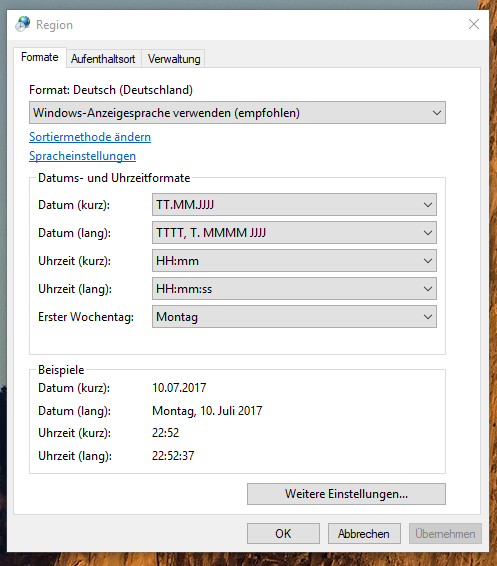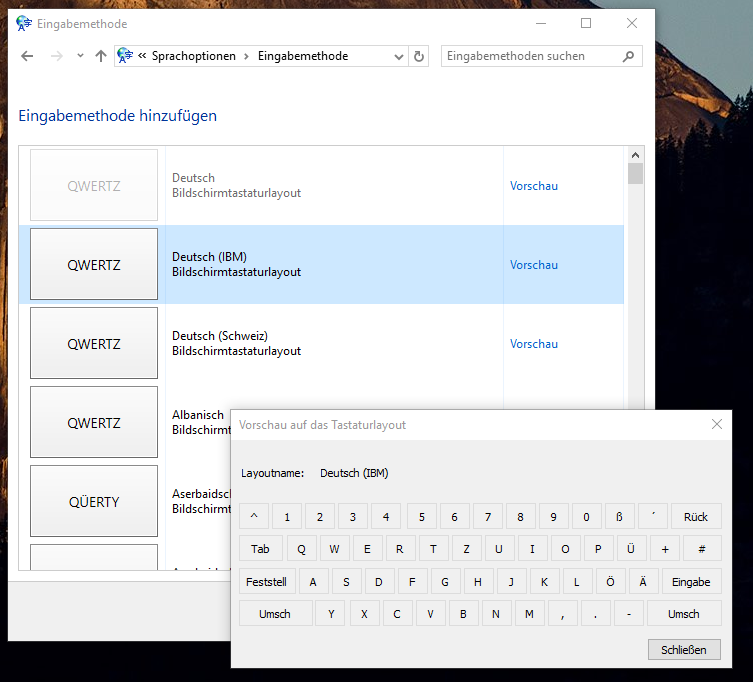
Das Versal-Eszett sieht aus wie eine Taube, die einen dicken Bauch hat.
Die Taube will mit ihren Flügeln das E umarmen, um sich an dessen Schulter auszuheulen ...
Nix Taube oder Robbe – das ist ein waschechter ẞ-Pinguin ;-)
Auf jeden Fall richtig übel.
Für das große ß reicht schon eine Tastatur nach T2, es wird durch Alt Gr und H gebildet. Allerdings verkauft momentan nur der Hersteller Cherry aus Auerbach in der Oberpfalz so ein Gerät in der T2-Version. […]
Die Tastatur-Firmen warten darauf, dass die DIN-Norm für die Standards aktualisiert wird. Momentan arbeiten der Normenausschuss Ergonomie und der Normenausschuss Informationstechnik und Anwendungen vom DIN an einer Lösung für das ß-Problem. Bis sie so weit sind, kann es aber noch einige Wochen dauern. Es soll Überlegungen geben, das Grad-Zeichen, also den kleinen hochgestellten Kreis, durch das große ß zu ersetzen, heißt es von der Firma Cherry. Damit befände sich das große ß am linken Rand der Ziffernleiste neben der Eins, das kleine wie gehabt am rechten Rand neben der Null.
Nun, schon vor einiger Zeit hatte ich ja schon einen modifizierten Tastaturtreiber im Programm:
Hier hatte ich mich für die Position Shift + AltGr + ß entschieden. Dieser Tastaturtreiber, bei dem ich auch das lange s auf AltGr + s und auch den ZWNJ auf AltGr - gelegt habe, sowie einige weitere Ligatuten und Sonderzeichen aus der Fraktur-Umgebung.
Leider lässt sich auf Windows10 kein soch privater Tastaturtreiber mehr installieren, aber meine Position des ẞ haben sie übernommen :-) Schade ſ und den ZWNJ hab ich da dann nicht mehr.
Aber immerhin hat ẞ da schon sein zuhause gefunden, und aus meiner Sicht ohne Umgewöhnung.
Mein Lieblingsplatz wär allerdings der Platz des "?" welches man ja auf AltGr+1 (also neben "!") verlagern könnte, dann wären ß und ẞ auf der gleichen Taste genau wie andere Buchstaben vereint. Eine andere Lösung: ß und ẞ werden auf die Taste neben ö, also # ' verlegt, und diese Zeichen rutschen auf den bisherigen Platz vom ß, wodurch ßẞ dann bei den Buchstaben lägen, wo sie eigentlich hingehören würden.
Ich finde die Belegung von Windows 10 am sinnvollsten. Das Zeichen ist dort, wo wir das ß sowieso wissen.
Ach ja, käme das Fragezeichen auf die 1-Taste als AltGr+1, könnte man auf Shift+AltGr+1 auch noch das Interrobang unterbringen, das hätte dann auch eine Logik.
Drum hatte ich mich ja für exakt die gleiche Lösung entschieden, ohne vorhandenes weg zu schubsen.
Bei meinem alternativen Tastaturlayout ist das ẞ da, wo es logischerweise hingehört, nämlich auf der Zweitbelegung von ß.
Für eine Qwertz-Belegung würde ich es entweder auf ß oder s packen.
Die Sache mit Windows 10 kann ich jetzt von meinem Rechner nicht beurteilen, da ich dies nicht installiert habe.
Nein, auf aktuellem Windows 10 Version 1703 kommst du nicht mehr auf die Auswahlseite mit den verschiedenen Tastaturlayouts. Hier ist nur noch eine Sprachauswahl, und Windows holt dann den betreffenden Tastaturtreiber von der Windows-Update Seite. Dafür ist aber ẞ offiziell auf Shift AltGr ß gekommen.
Bei Build 1607 ging es noch.
Dieses Fenster gibt es nicht mehr:
Statt dessen hat die Systemsteuereung bei Region nur noch dies:
und die Sprachoptionen - Eingabemethode bietet nur das:
Nur die Windows-eigenen Tastaturlayouts, und in der Vorschau sieht man auch nicht die Shift/AltGr-Belegung.
Auf der Mac-Tastatur wäre bei alt-shift-w noch Platz (da wäre es immerhin in Nachbarschaft zum ∑) ... da ist jetzt bloß eine von diesen nervigen Anführungszeichen-Dopplungen :party:
M.E. ist der Ascii-Zirkumflex auf der Taste ganz li. oben [°] für die deutsche Tastatur entbehrlich.
Wie findest Du diesen Vorschlag?
Ich vertraue darauf, dass die Beteiligten des Normenausschusses wissen, was sie tun und die Vor- und Nachteile und technischen Erfordernisse gut abwägen. Ohne dieses Hintergrundwissen möchte ich mir dazu keine Meinung bilden.
Moi, je suis né à Brême ... allein schon darum braucht man das ;-) Spaß beiseite: französiche Texte, Ersatz für den Längenstrich z.B. in japanischen  Transkriptionen – mir fallen auf Anhieb viele Alltagsverwendungen für den Zirkumflex ein.
Ich bin in diesen Kodierungssachen ja völlig ahnungslos. Wahrscheinlich gibt es eine simple Erklärung. (Ich benutze Windows 7 und die neueste Firefox-Version bzw. Version 5.2.1.2 von LibreOffice, falls das für die Problemlösung relevant ist.)